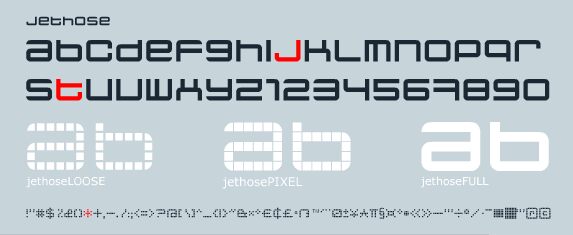
Jethose PIXEL von Transporter ist eine digitale Pixel-Schriftart. Jedes Zeichen ist aus kompakten, kachelartigen Rechtecken aufgebaut, die sich in einem klaren Raster anordnen und durch abgerundete Ecken weichgezeichnet werden – das verleiht ihr einen mechanischen und zugleich angenehm freundlichen Charakter. Das Ergebnis wirkt wie leuchtende Segmente auf einem Retro-LED-Panel: gestochen scharf, modular und bereit für großformatige Anwendungen, ohne den technischen Touch zu verlieren.
Mit Jethose PIXEL verleihst du Spiele-Logos, Sci-Fi-Postern, DJ- oder EDM-Flyern, Tech-Event-Branding, Motion-Graphics-Titeln und Streaming-Overlays einen starken digitalen Puls. Diese kostenlose Schriftart glänzt besonders bei großen Größen, wo ihr blockartiger Rhythmus und das präzise Spacing voll zur Geltung kommen. Kombiniere sie für begleitenden Text mit einer schlichten geometrischen Sans, um das Layout übersichtlich und lesbar zu halten.